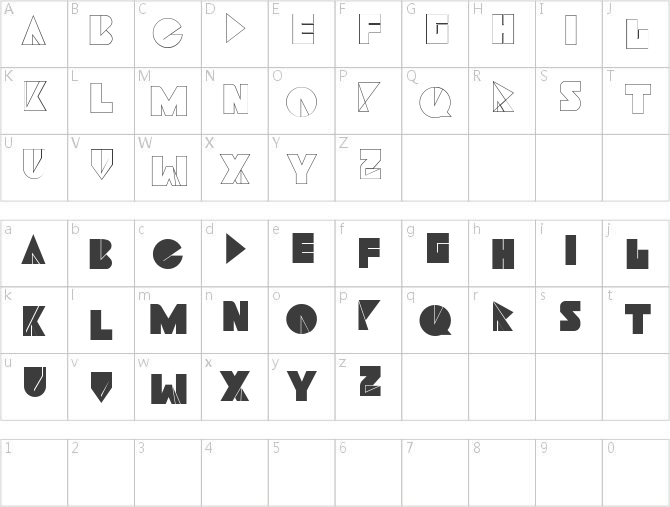
字體名稱: Navia-T
Navia-Type-Thin
Navia-Type-Thin介紹
Navia-Type-Thin字體字庫是一款讓人賞心悅目、百看不厭的英文字體,適合各類廣告和產(chǎn)品包裝設(shè)計(jì)應(yīng)用,字體大小0.01MB,格式為ttf字體,上傳用戶是華大文化傳媒,作者/版權(quán)方為未知